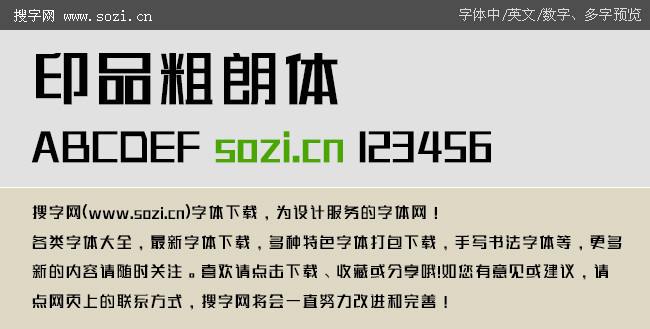
印品粗朗體
搜字網(wǎng)給大家提供一款印品粗朗體中文字體下載,印品粗朗體字體具有很強的識別度,并且也極具現(xiàn)代感,字體字形筆畫粗壯,整齊劃一,在筆畫的形狀上把橫畫加粗且把宋體字的聳肩角削平為等線狀,同時又保留了宋體字的尖頭細尾和頭尾粗細不一的特質(zhì),大大削弱了視覺上的厚重感。適用于搭配標志、廣告標語、商業(yè)廣告等廣告設(shè)計。